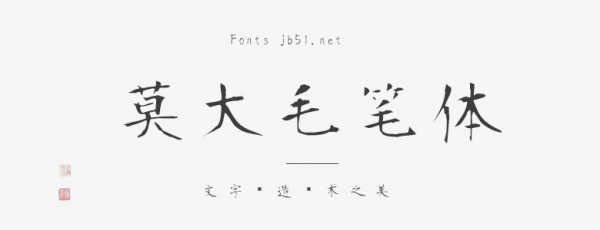
莫大毛筆體是基于衡山毛筆體的開放原始碼中文字型增加更多字重的字數(shù)的修改版字體。衡山毛筆字體是來自于日本書法家青柳衡山,目前字型內(nèi)文字和符號字數(shù)在:14,321個。
與衡山毛筆體體有何不同?
1、增加了更多中文字體
莫大毛筆體補齊臺灣教育部列出的4,808個常用字,在原本的衡山毛筆字體架構下,莫大毛筆字體增加(和修改)168個字。
2、增加了字體字重,現(xiàn)在總共5個字重
原本的衡山毛筆字體放在Regular字重裡,現(xiàn)在透過程序自動產(chǎn)生ExtraLight、Light、Medium、Bold 新的字重。Light字重是把原本的KouzanBrushFont微微調(diào)細一點點。在ExtraLight的字重裡,可能會因為筆劃太細造成某些筆畫消失。在Medium和Bold的字重裡,可能會因為筆劃太粗造成某些筆畫重疊難以識別,有粗體字的需求,可以先挑戰(zhàn)使用Bold字重看看,如果發(fā)現(xiàn)效果不如預期,再改用Medium字重。
不能確定自動產(chǎn)生出來的字重裡每一個都是完整的字,畢盡程式會誤判是常有的事情,所以不是在Regular字重裡的筆劃可能會消失。
3、清除衡山毛筆字體裡空白的文字
衡山毛筆字體裡有很多空白的字, 會造成無法讓系統(tǒng)自動用預設字體來補字,已清除空白的文字。
4、調(diào)整標點符號位置
衡山毛筆字體的全形標點符號針對日本做設計,調(diào)整為臺灣常見的置中用法。半形的backslash,調(diào)整為非日本地區(qū)用法。
5、增加部分臺灣口語出現(xiàn)的中文字和增加部份的粵語字